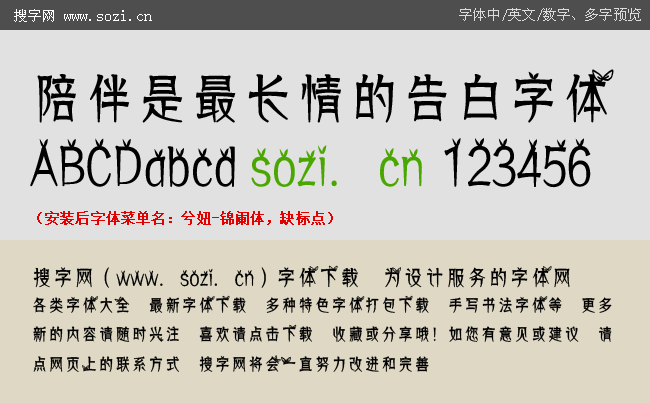
陪伴是最長(zhǎng)情的告白字體
搜字網(wǎng)給大家提供一款陪伴是最長(zhǎng)情的告白字體手機(jī)中文字體下載。這款手機(jī)字體是在方正懸針篆變簡(jiǎn)體筆畫間插入了漂亮的卡通圖案。方正懸針篆變字體意在保留篆書韻味,同時(shí)將隸書與楷書筆畫特征熔于一爐,實(shí)為三種書體的統(tǒng)一。將傳統(tǒng)書法藝術(shù)與現(xiàn)代形式語(yǔ)匯融合,追求裝飾性及藝術(shù)美感,端莊秀美、開(kāi)張疏朗,雍容大氣、復(fù)古卻易讀。加入了卡通圖案后又增添了趣味性,特別適合喜歡手機(jī)字體個(gè)性一些的朋友在手機(jī)上安裝使用。